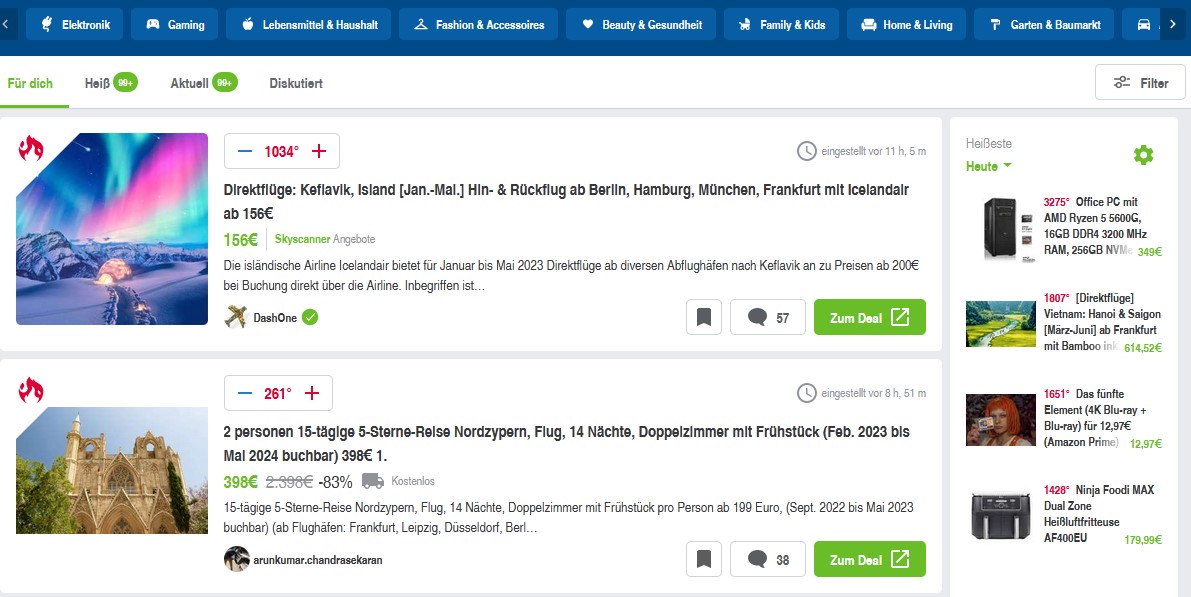
Probleme mit manchen Schriftarten
ich habe heute den Rechner eingeschaltet und nachdem ich eine bestimmte Internetseite aufgerufen hatte, habe ich sofort gemerkt, dass die Schriftart dort seltsam anders ausschaut! Der Text wirkt zusammengestaucht - ich habe ein Screenshot gemacht:
die Seite "mydealz.de". Man erkennt, dass die Texte wie zusammengestaucht aussehen. Auch auf meiner lokalen iobroker Instanz betrifft dies die Schrift von der Adminansicht.
Am Rechner selber hatte ich eigentlich nichts groß verändert außer am Sontag Solid Edge 23 CE installiert. Scheinbar heute wurden auch paar Apps aktualisiert, wobei ich keine Ahnung habe woher das Age of Empires III kommt? Könnte sein, dass dies mal irgendwo kostenlos abzustauben war aber gespielt habe ich es noch nie...
Mich würde nun interessieren ob vielleicht jemand ähnliches Phänomen hat und weiß wie ich die Schriftarten wieder zurechtbiegen kann? Ich habe mal mit dem Firefox Web Entwickler Tool gespielt und es scheint zumindest die Schriftart "Helvectica" zu betreffen...
Gab letzte Woche dasselbe Problem. Scheinbar musst du nur eine bestimmte Schrift Deinstallieren damit alles wieder geht
okay ich habe mal Helvectica gelöscht und jetzt passt es wieder!